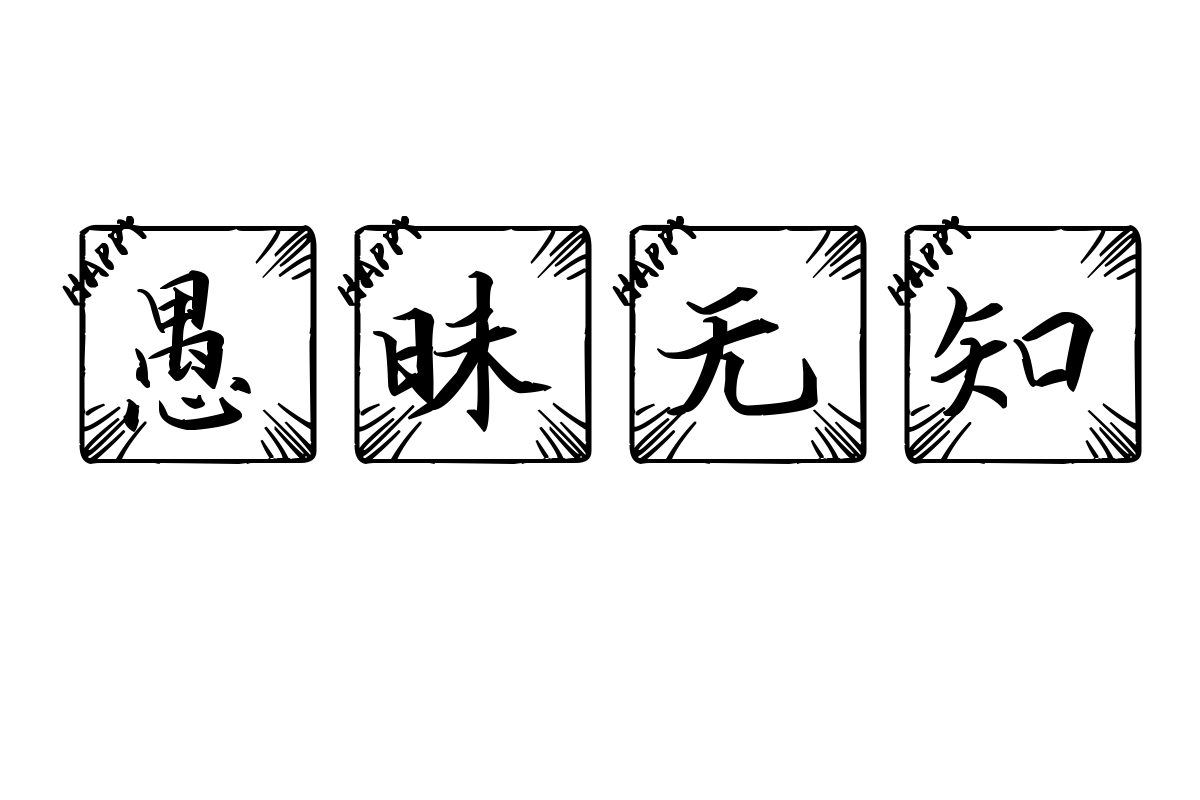
汉呈心花怒放是一款具有中国传统美感的字体。这款字体的设计灵感来源于中国的传统绘画和书法艺术,通过将汉字的结构、笔画和形态进行巧妙的组合和创新,形成了一种独特的视觉效果。
汉呈心花怒放的字体特点如下:
1. 字体结构:这款字体采用了传统的汉字结构,包括横、竖、撇、捺等基本笔画,以及各种复杂的组合和变化。这种结构使得字体既有传统韵味,又不失现代感。
2. 笔画风格:在保持传统汉字笔画的基础上,汉呈心花怒放的字体对某些笔画进行了简化和变形,使其更加简洁、流畅。同时,也保留了一些传统笔画的特点,如钩、点、折等,使得整体效果更加丰富。
3. 字形设计:汉呈心花怒放的字体在字形上进行了大胆的创新。例如,将一些常见的汉字拆分成多个部分,形成独特的形状;或者将一些笔画进行重叠和交错,形成新的视觉效果。这些设计使得字体更加独特、有趣。
4. 色彩搭配:汉呈心花怒放的字体在色彩上进行了精心搭配。通常采用黑色作为主色调,以突出文字本身的效果;同时,也会适当加入一些鲜艳的色彩,如红色、黄色等,以增加视觉冲击力和活力。
总之,汉呈心花怒放是一款具有浓厚中国传统特色的字体,既保留了汉字的基本结构和美感,又通过笔画、字形和色彩等方面的创新,展现出独特的视觉效果。这款字体适用于各种需要展示中国传统文化和艺术氛围的场景,如广告、海报、网页设计等。